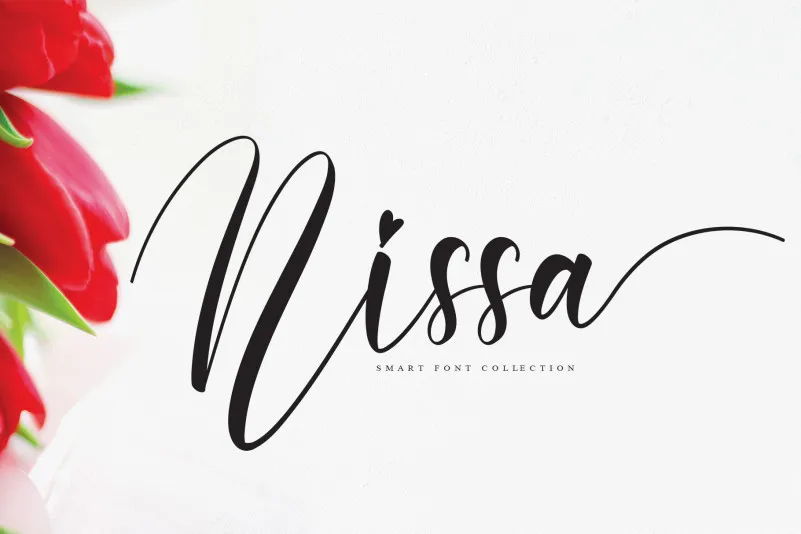
Nissa Font – Download Grátis
A Nissa Font é uma elegante serif que adicionará um toque sofisticado a seus projetos. Seja para criar logotipos profissionais ou marcas de rótulos, este script gráfico brilha com sua cuidadosamente construída tipografia. Não apenas atende à necessidade dos rótulos e watermarks, mas também ilustra seu potencial em criar belas criações digitais que exalam elegância e sofisticação. Com Nissa Font, você pode experimentar a arte do design com uma nova perspectiva, transformando cada projeto de um nível ao outro.